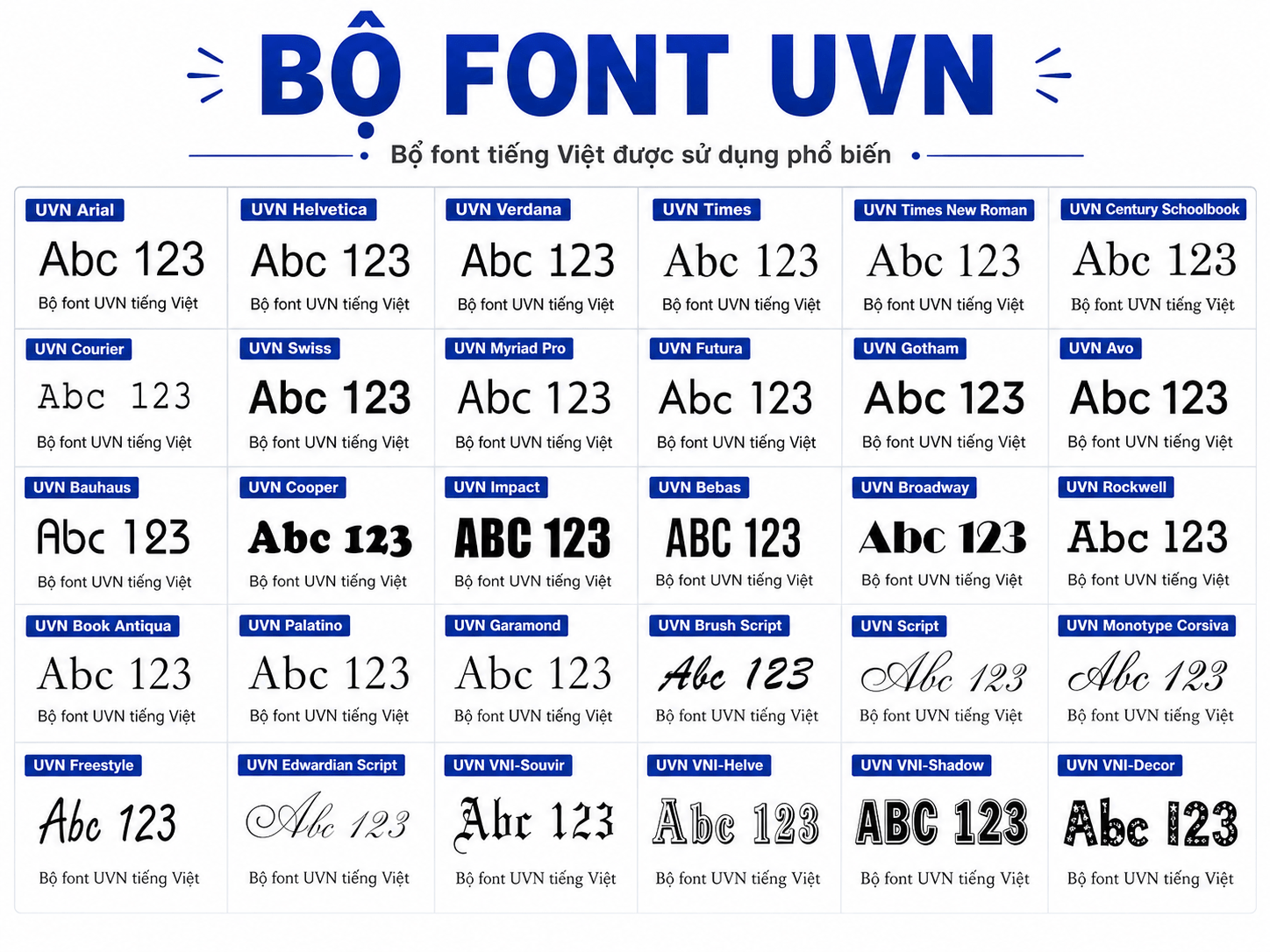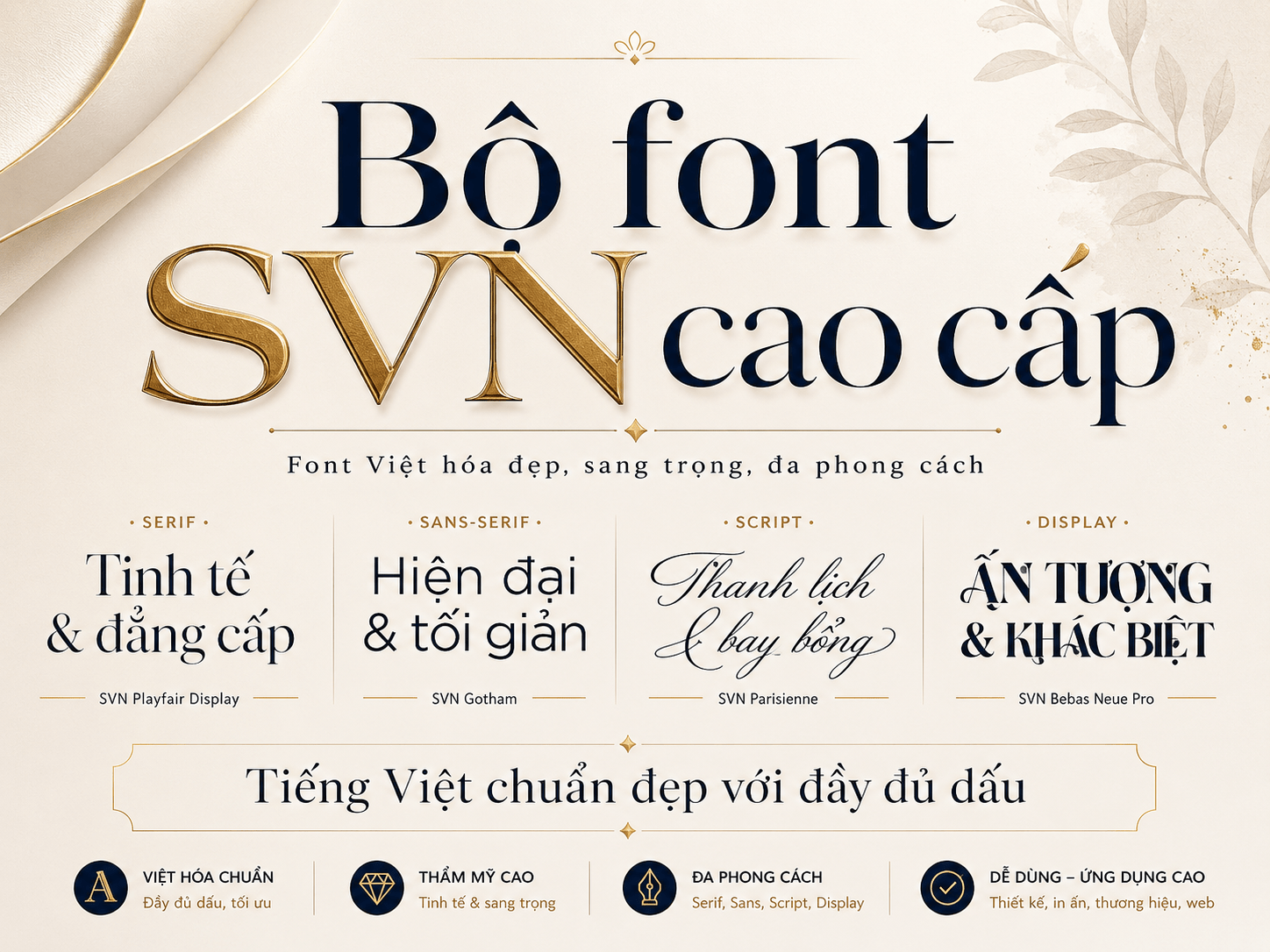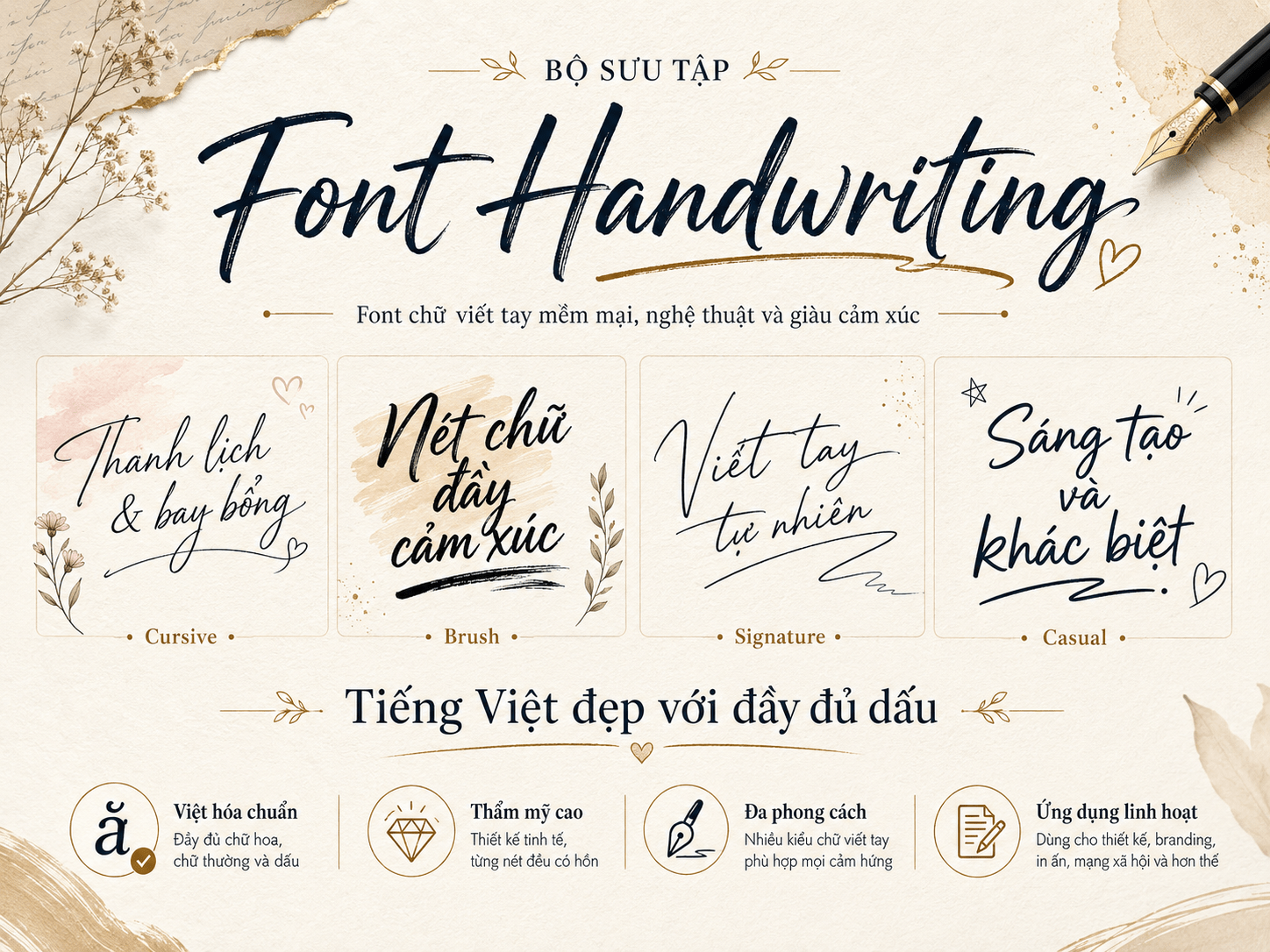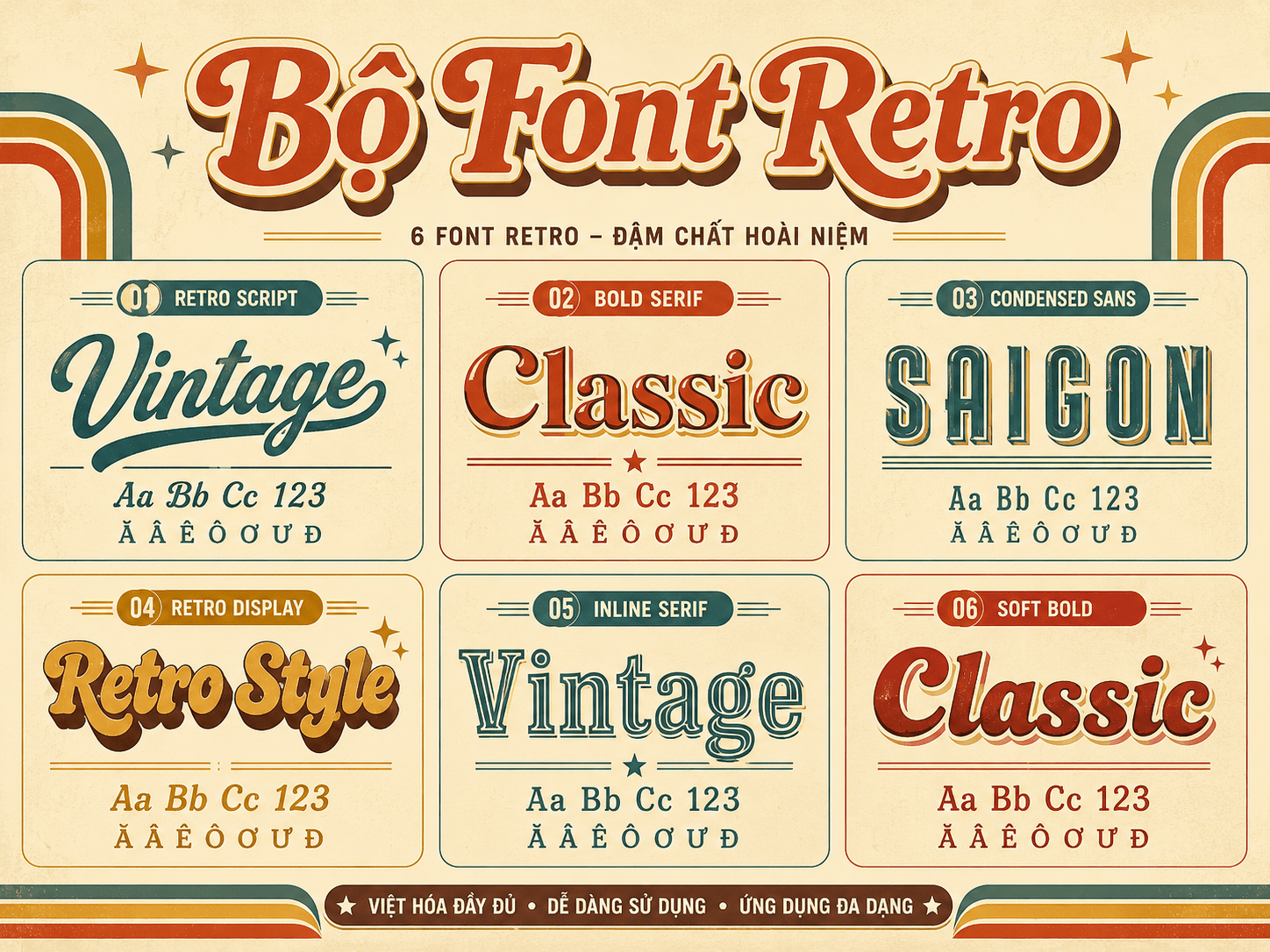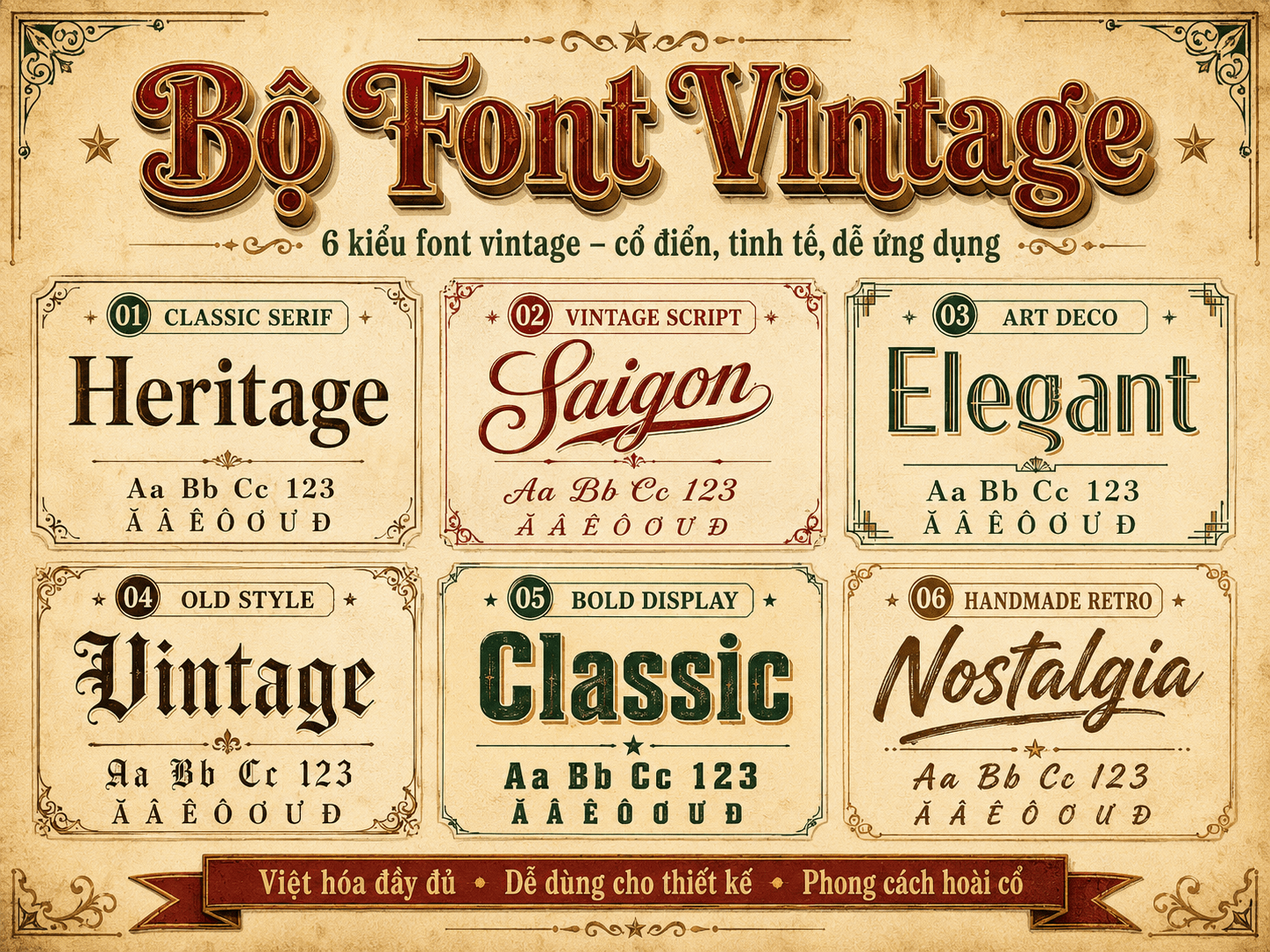
Trong thiết kế đồ họa và sáng tạo nội dung, một hình ảnh đẹp hay thông điệp hấp dẫn vẫn chưa đủ để giữ chân người xem. Cách bạn lựa chọn và trình bày font chữ mới là yếu tố giúp câu chữ trở nên nổi bật, dễ đọc và có sức hút hơn. Bài viết này sẽ giới thiệu đến bạn những font chữ đẹp được ưa chuộng hiện nay, đồng thời hướng dẫn cách sử dụng chúng hiệu quả trong từng thiết kế.
Tại sao Font chữ lại quyết định 80% sự thành công của thiết kế?
Bạn có bao giờ thắc mắc tại sao cùng một câu nói, đặt trên nền ảnh giống nhau, nhưng thiết kế của người khác trông vô cùng sang trọng, còn của mình lại có vẻ “nghiệp dư”? Câu trả lời nằm ở Typography (Nghệ thuật sắp chữ). Font chữ chính là giọng nói của văn bản. Một font chữ thanh mảnh mang lại cảm giác tinh tế, trong khi một font chữ đậm, góc cạnh lại thể hiện sự mạnh mẽ và hiện đại.
Bước sang năm 2026, xu hướng thiết kế tiếp tục hướng tới sự tối giản kết hợp với các dòng font Serif hiện đại để tạo điểm nhấn. Dù bạn là một Designer chuyên nghiệp, một Marketer, hay chỉ đơn giản là muốn làm một video TikTok thật “cuốn”, việc sở hữu một bộ font chữ đẹp là điều bắt buộc.
Những lưu ý quan trọng khi chọn font chữ trong thiết kế
Khi thiết kế website, ấn phẩm truyền thông hay tài liệu chuyên nghiệp, font chữ không chỉ quyết định yếu tố thẩm mỹ mà còn ảnh hưởng trực tiếp đến trải nghiệm đọc và khả năng truyền tải thông điệp. Một font chữ phù hợp sẽ giúp nội dung rõ ràng, dễ tiếp cận và tạo cảm giác chuyên nghiệp hơn. Dưới đây là những điểm bạn nên lưu ý khi lựa chọn font chữ cho thiết kế.
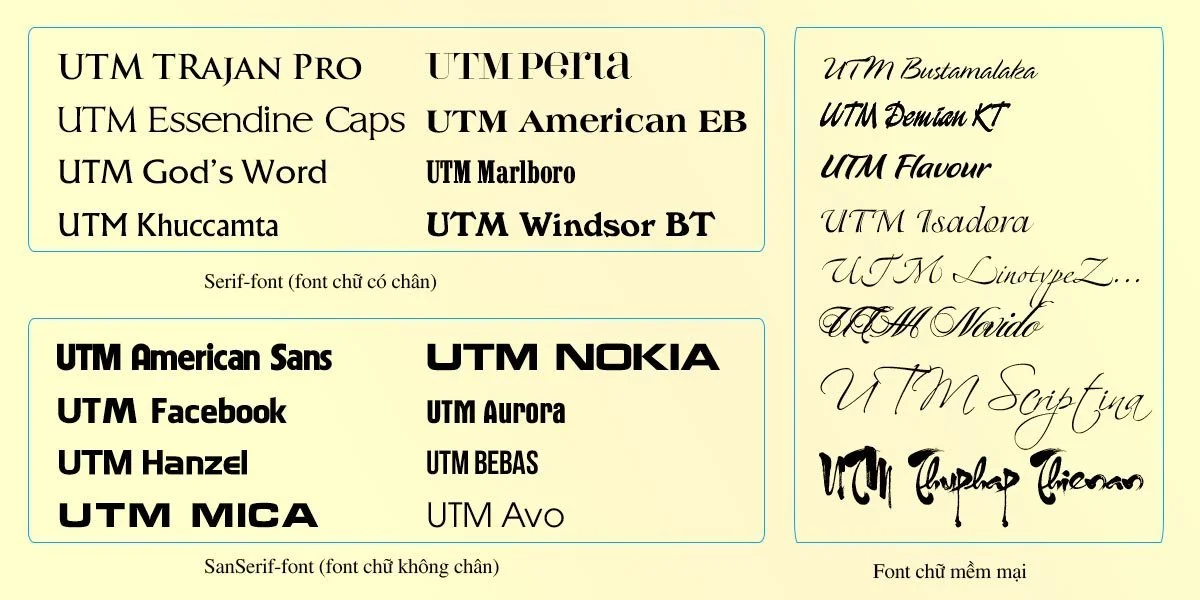
Hạn chế dùng quá nhiều font chữ
Không nên sử dụng quá nhiều kiểu font trong cùng một thiết kế. Việc kết hợp nhiều font khác nhau dễ khiến bố cục trở nên rối mắt, thiếu đồng nhất và làm giảm tính chuyên nghiệp.
Thông thường, bạn chỉ nên dùng từ 2 đến 3 font chữ trong một thiết kế. Ví dụ: một font cho tiêu đề, một font cho nội dung chính và một font phụ nếu cần nhấn mạnh. Cách này giúp tổng thể hài hòa, dễ nhìn và giúp người đọc tiếp nhận thông tin tốt hơn.
Ưu tiên các font chữ có cùng phong cách
Khi phối hợp nhiều font chữ, bạn nên chọn những font có phong cách tương đồng. Điều này giúp thiết kế giữ được sự nhất quán và tránh cảm giác lệch tông.
Ví dụ, nếu tiêu đề sử dụng font hiện đại, phần nội dung cũng nên dùng font có nét đơn giản, gọn gàng và phù hợp với tinh thần thiết kế. Sự đồng bộ này giúp website hoặc tài liệu trông chuyên nghiệp, chỉn chu và dễ tạo thiện cảm với người xem.
Chọn font chữ dễ đọc
Một thiết kế đẹp nhưng khó đọc sẽ làm giảm hiệu quả truyền tải nội dung. Vì vậy, yếu tố dễ đọc luôn cần được ưu tiên khi chọn font chữ.
Với các đoạn văn dài, bạn nên dùng font sans serif vì kiểu chữ này thường hiển thị rõ ràng trên màn hình. Ngoài ra, cần chú ý đến kích thước chữ, khoảng cách dòng và khoảng cách giữa các ký tự. Những yếu tố này giúp người đọc cảm thấy thoải mái hơn khi theo dõi nội dung.
Tránh font chữ quá đậm hoặc quá mảnh
Font chữ quá đậm có thể khiến thiết kế trở nên nặng nề, tạo cảm giác bí và khó chịu khi đọc lâu. Ngược lại, font quá mảnh lại dễ bị nhòe, khó nhìn, đặc biệt trên màn hình nhỏ hoặc thiết bị có độ phân giải thấp.
Lựa chọn an toàn là các font có độ dày vừa phải. Kiểu font này giúp nội dung hiển thị rõ ràng, cân bằng và phù hợp với nhiều loại thiết kế khác nhau.
Nên dùng font chữ có độ rộng vừa phải
Độ rộng của font cũng ảnh hưởng nhiều đến trải nghiệm đọc. Font quá hẹp có thể khiến chữ bị nén lại, gây khó đọc. Font quá rộng lại dễ làm bố cục mất cân đối và thiếu sự tinh gọn.
Bạn nên chọn font có độ rộng trung bình để nội dung hiển thị thoáng, dễ theo dõi và giữ được vẻ chuyên nghiệp cho tổng thể thiết kế. Đây là lựa chọn phù hợp cho cả website, banner, tài liệu quảng cáo và các ấn phẩm truyền thông.
Top 30+ Font chữ đẹp việt hóa mới nhất 2026
Dưới đây là tuyển tập những bộ font chữ đẹp, dễ dùng và có tính ứng dụng cao trong thiết kế. Đặc biệt, các bộ font này đều có phiên bản Việt hóa, giúp bạn gõ tiếng Việt có dấu rõ ràng, hạn chế lỗi hiển thị và phù hợp với nhiều mục đích sử dụng khác nhau.
Bộ Google Fonts Việt hóa: Roboto, Montserrat, Open Sans
Google Fonts là nhóm font gần như không thể thiếu đối với designer, marketer, content creator hay người làm website. Những font như Roboto, Montserrat, Open Sans được thiết kế tối ưu cho khả năng hiển thị trên màn hình, giúp nội dung rõ ràng, hiện đại và dễ đọc.
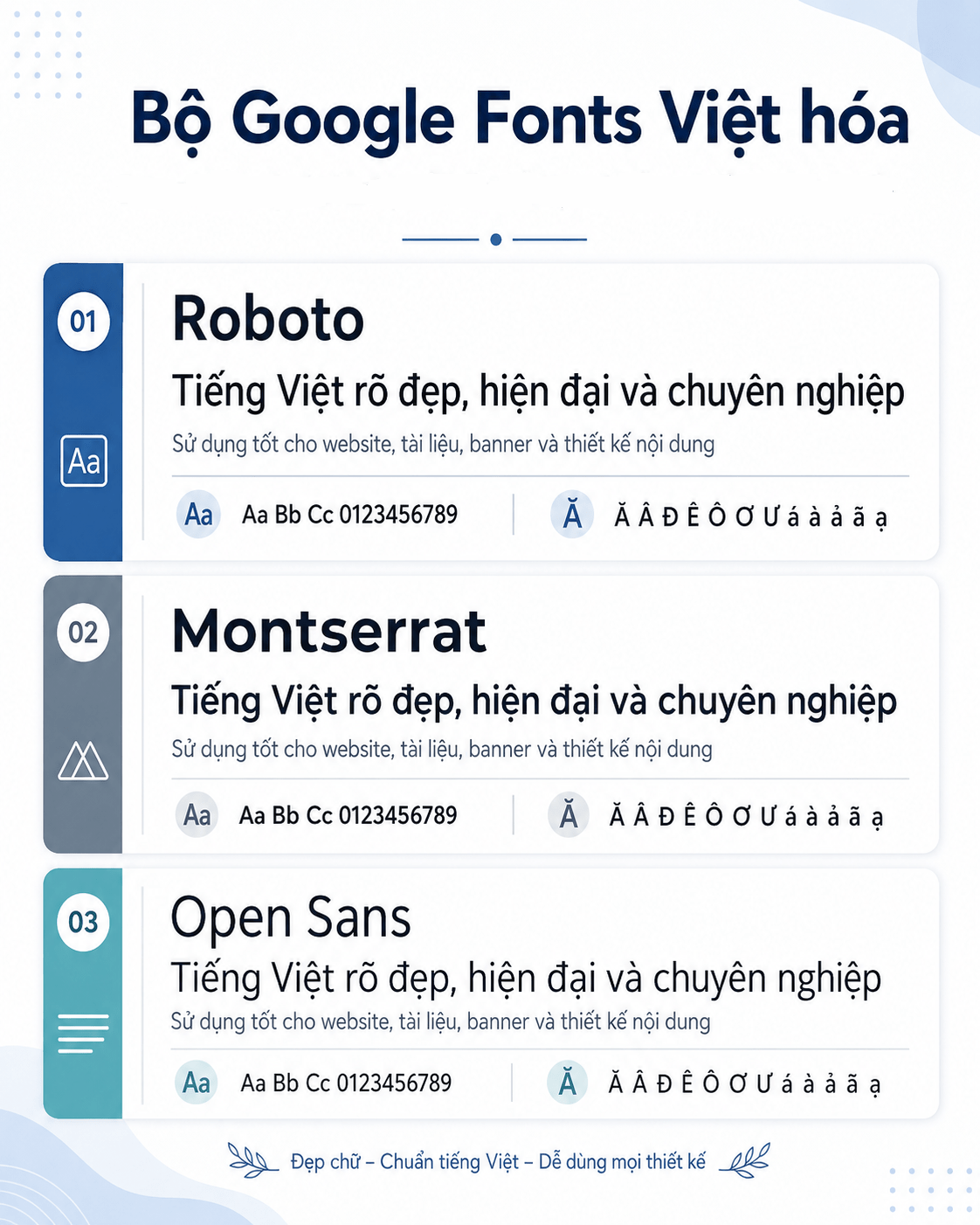
Ưu điểm lớn của nhóm font này là sự an toàn và linh hoạt. Bạn có thể dùng cho website, banner, slide thuyết trình, tài liệu văn phòng hoặc thiết kế thương mại mà vẫn giữ được cảm giác chuyên nghiệp. Ngoài ra, Google Fonts còn miễn phí và tương thích tốt với hầu hết nền tảng thiết kế hiện nay.
Bộ font UTM và UVN quen thuộc
UTM và UVN là hai bộ font rất phổ biến tại Việt Nam, đặc biệt trong lĩnh vực in ấn, quảng cáo và thiết kế truyền thống. Dù đã xuất hiện từ lâu, hai bộ font này vẫn được nhiều người sử dụng nhờ sự đa dạng về phong cách và khả năng ứng dụng cao.